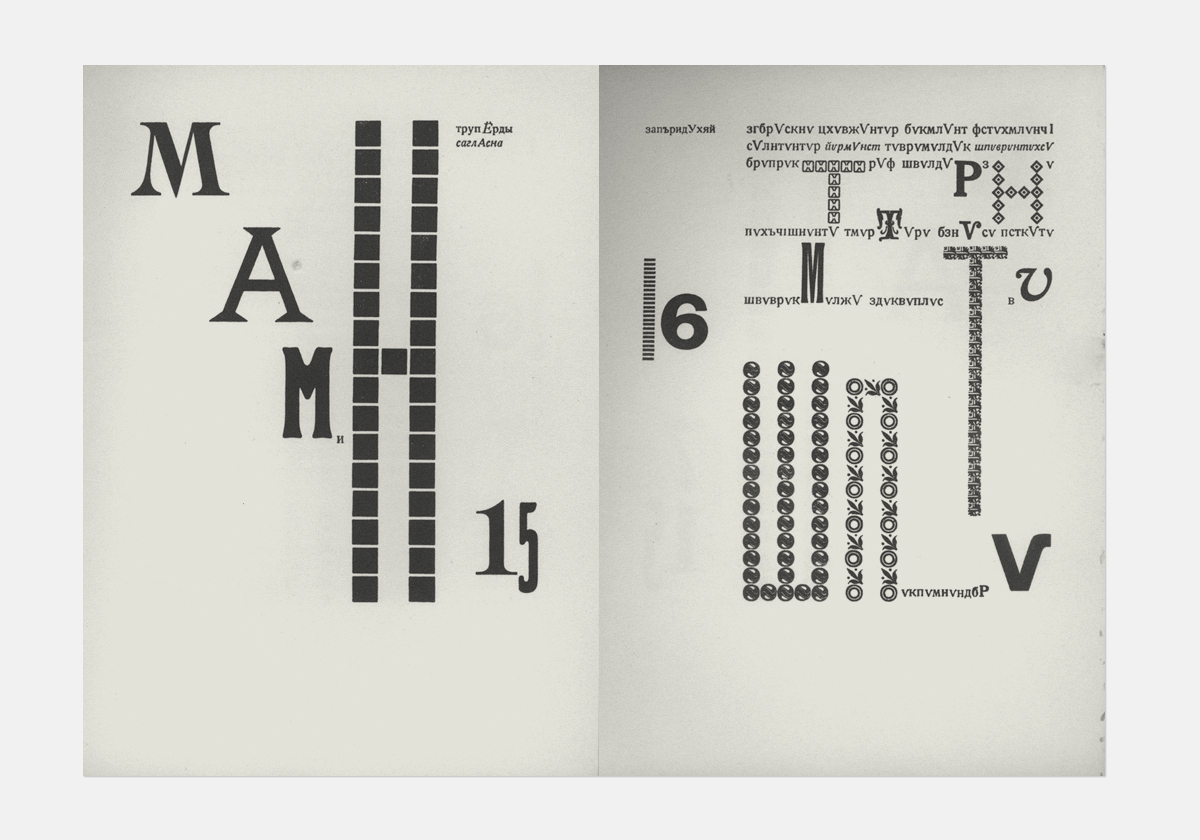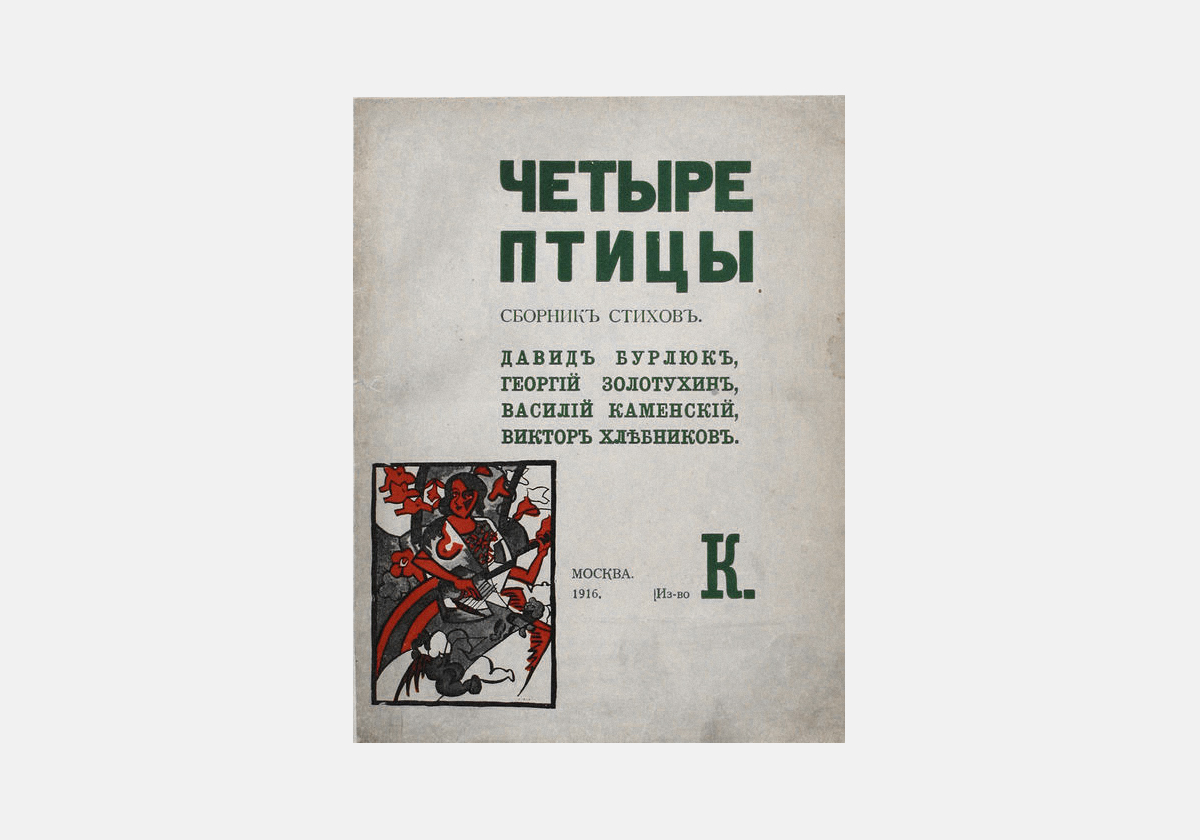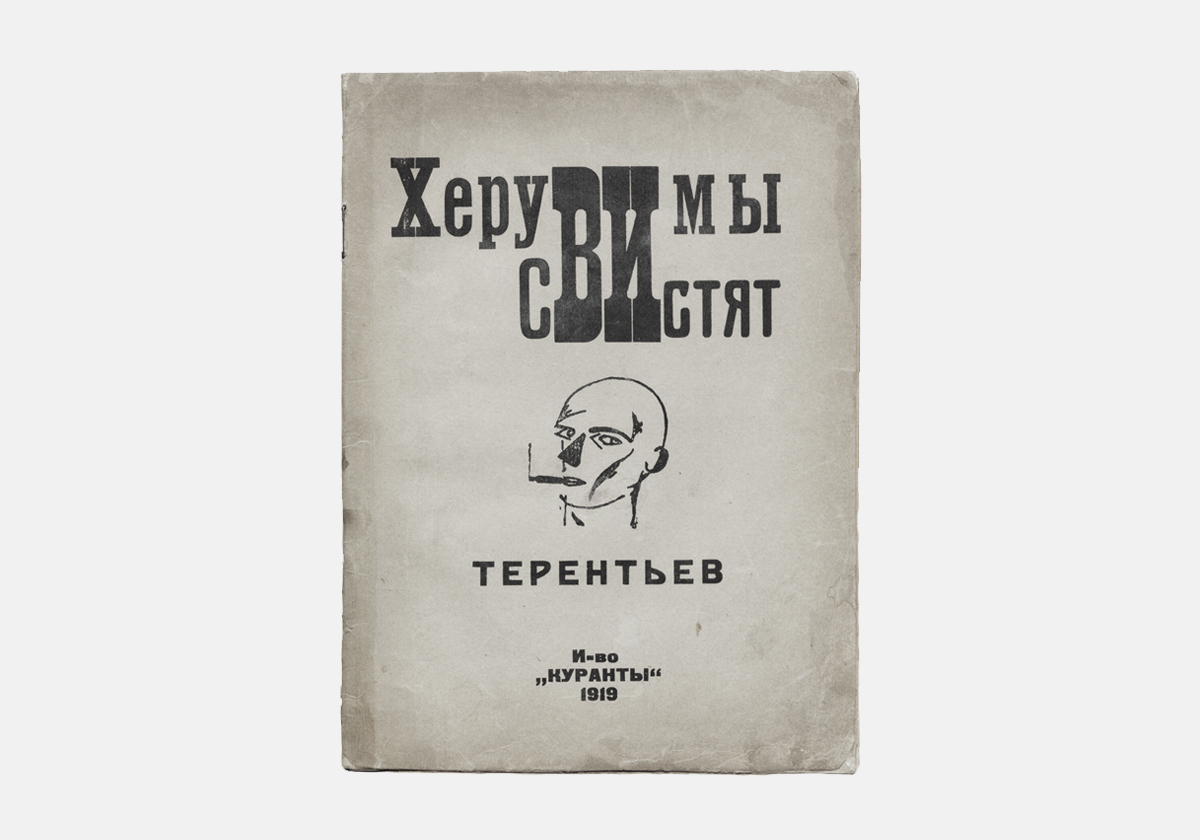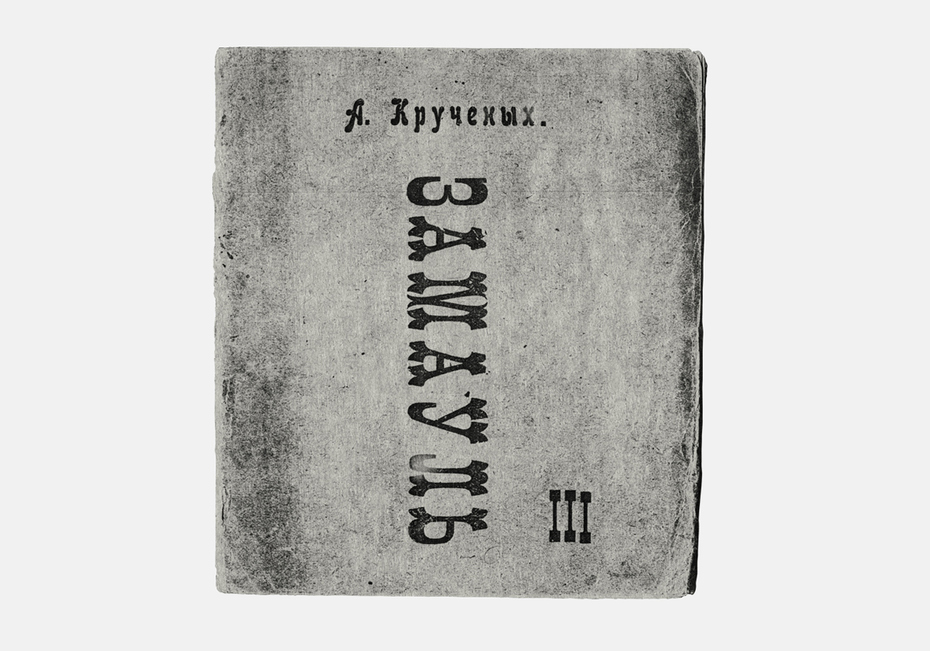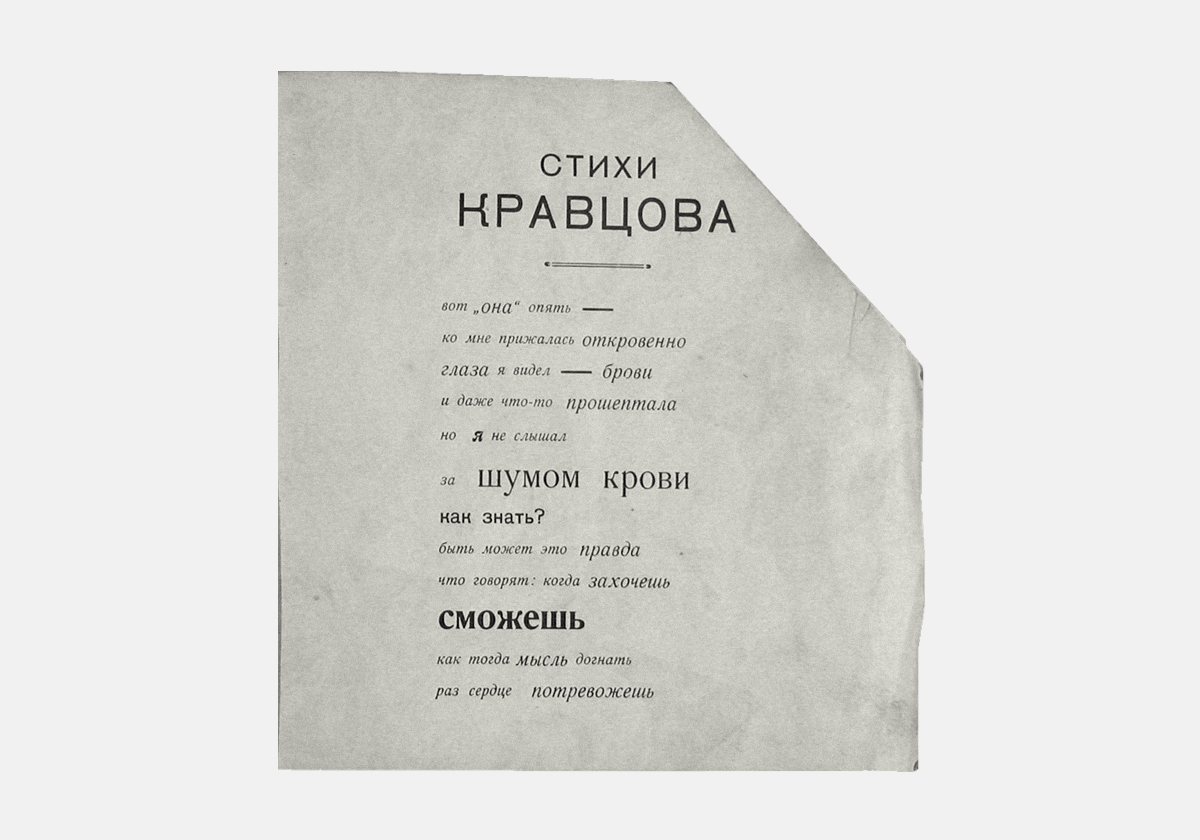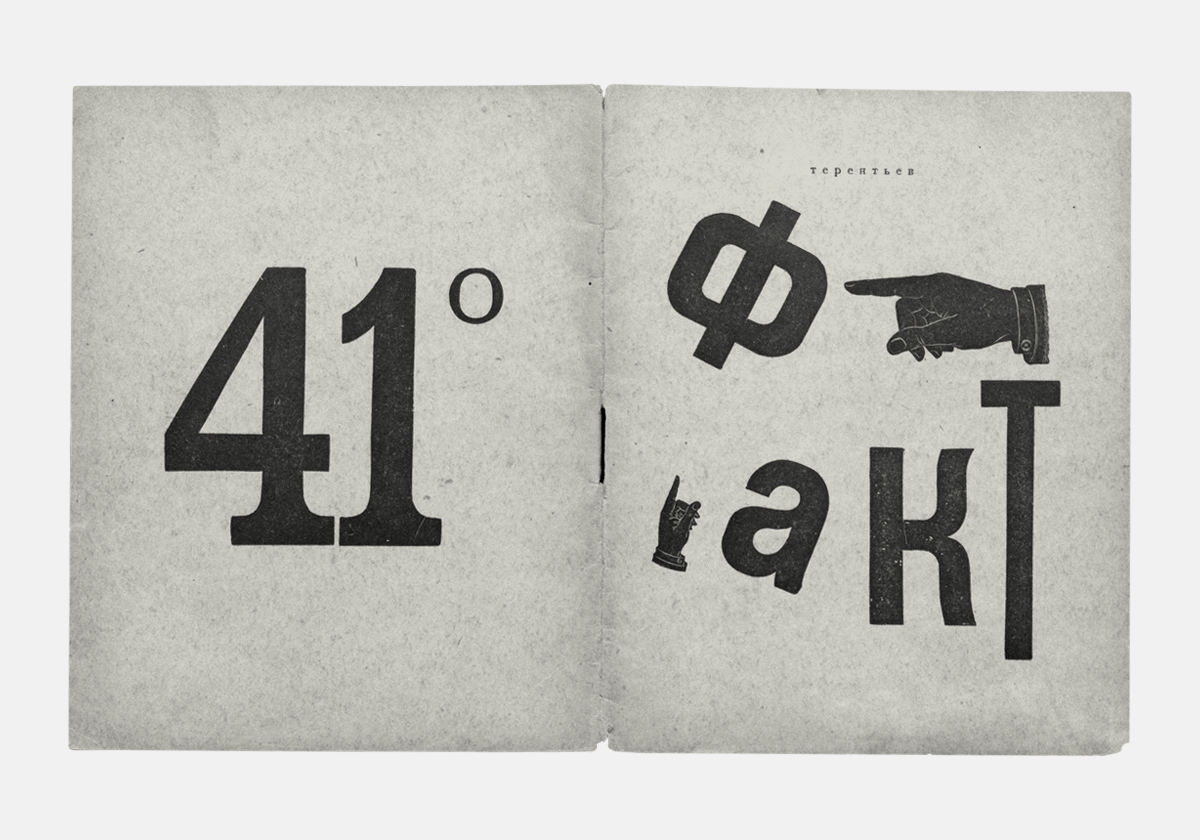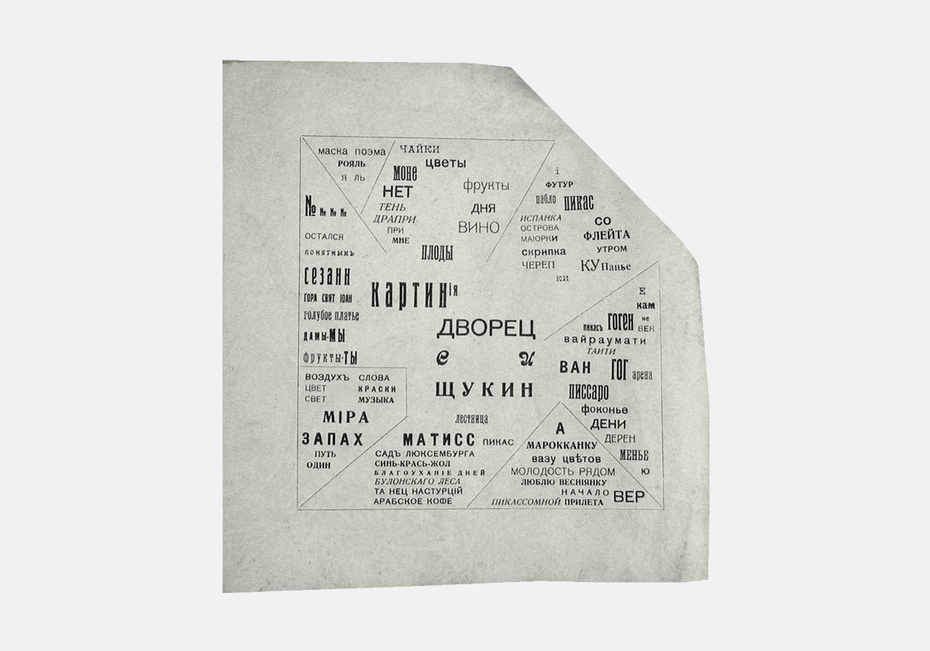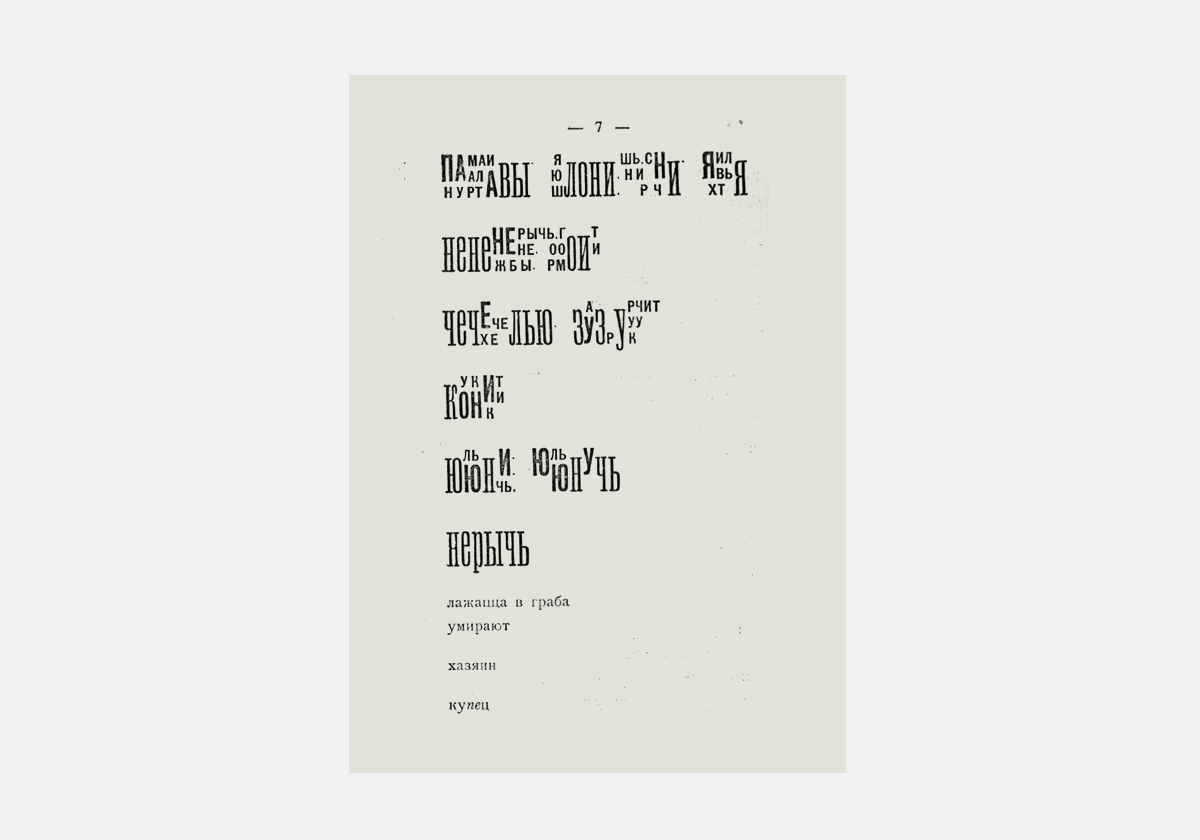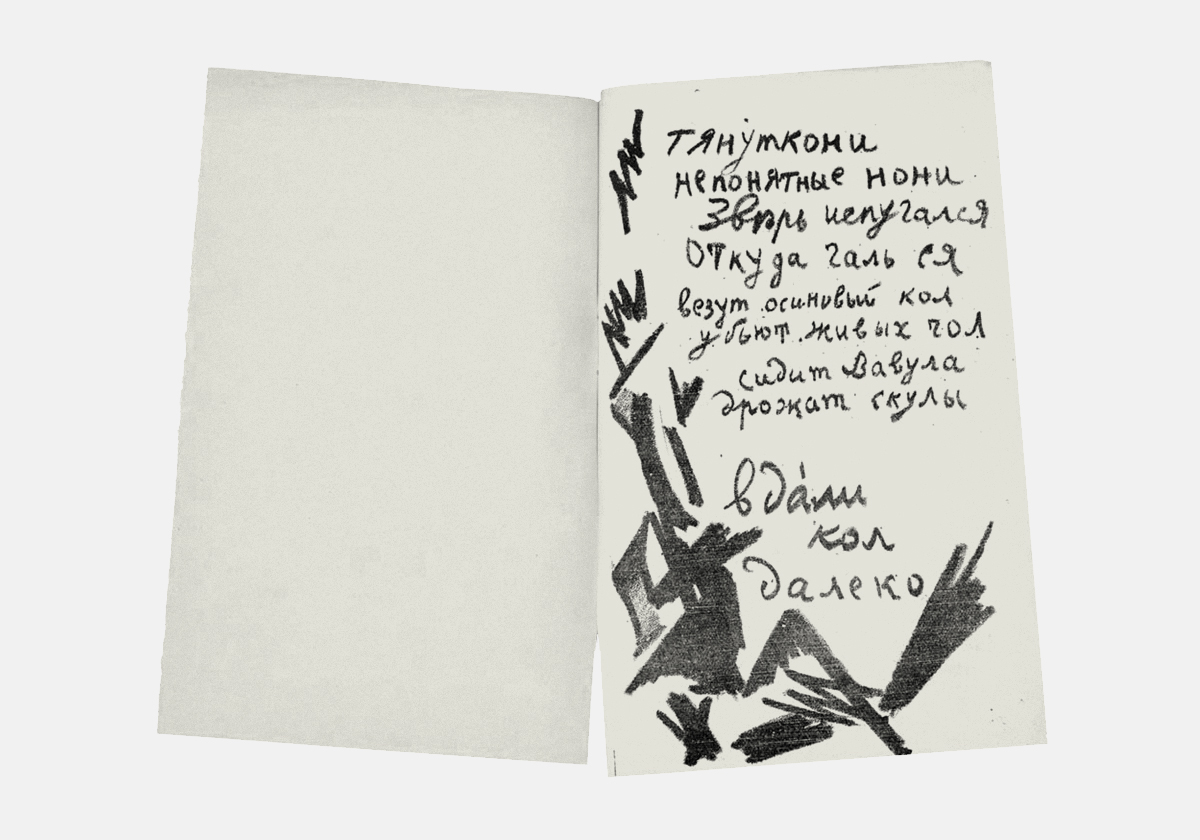
Типографика футуристов
на взгляд типографа*.
Часть вторая
Владимир Кричевский
итателю предлагается вторая часть статьи, написанной Вла­ди­ми­ром Кри­чев­ским, ав­то­ром из­вест­ных книг «Ти­по­гра­фи­ка в тер­ми­нах и об­ра­зах», «Пе­чат­ные кар­тин­ки ре­во­лю­ции», «По­э­ти­ка ре­про­дук­ции», «Мо­дерн(ъ) в пе­ча­ти», ис­сле­до­ва­те­лем рус­ско­го гра­фи­че­ско­го ди­зай­на на­ча­ла XX ве­ка. Первая часть статьи была опубликована в журнале в прошлом году.
"Типо" versus «лито»
Как графические техники типографика и литография — старые конкуренты.
Небывалое оживление в типографике XIX века косвенно связано с изобретением и развитием литографии. «Когда литография помимо приготовления новых образцов, сделавшихся необходимыми в общежитии благодаря удобству выполнения, начала отнимать у типографа его старые работы, к которым он давно привык, последний собрался с духом и бросился в бой со своей сестрою, в бой, становившийся всё более и более жестоким», — так писалось в 1900 году в популярном пособии по акциденции.
Действительно, многие наборные шрифты и орнаменты создавались тогда по образу и подобию литографированных, а вместе с вычурными буквами заимствовались и прихотливые формы построения надписей. Овальные, извилистые, ломаные, косые, поперечные строки стали обыденными. Металлический наборный материал подвергался известному насилию, что давало повод говорить об упадке типографского искусства. «Это всего лишь обманчивая имитация литографских эффектов посредством типографики, мнимая победа типографики над литографией», — заметил Ян Чихольд, комментируя французский типографический альбом 1862 года.
К началу XX века «упадок» стал ощущаться ещё острее, и футуристы словно бы решили взять реванш за мнимое поражение литографии, отменив типографику, образно говоря, росчерком литографского карандаша: из-под пера в печать, минуя набор.
Был в этом, разумеется, и другой смысл: желание предельно сблизить фактуры текста и рисунка, забота о передаче «движения души» пишущего, наконец, заманчивая возможность сосредоточить весь графический процесс в руках художника.
Протестуя против якобы холодного и обезличивающего набора, одни (Ларионов, Гончарова) воспользовались почти своим почерком, другие принялись форсировать небрежность и инфантильность письма, стараясь написать как можно косее и «каракулеватей» (больше всех в этом преуспел Крученых), третьи — это уже «лино» — гравировали на линолеуме, не стремясь превысить класс работ школьников с ластиками, четвёртые изобретали нарочито странные «принтскрипты» (как, например, Каменский в «железобетонах» тифлисского сборника 1918 года).
Артистизм этих опытов не стоит переоценивать: некоторые авторы «зависли» между живым и нарочито корявым почерком, доказав тем самым, что и антикаллиграфичность требует каллиграфической хватки (Взорваль — 1913, Тэ ли лэ или, например, хлебниковский Изборник работы П.Н. Филонова — обе 1914).
Коротенький экскурс в футуристическое «литописьмо» нужен, чтобы оттенить
достижения нескольких героев, отдавших предпочтение набору.
Отказ от набора — сильный «одномоментный» жест. То, что предлагалось взамен, можно найти и в черновиках пылких авторов (хотя бы у Пушкина), и в конспектах неаккуратных студентов. Тем же, кто выбрал набор, предстояло нарушить его вековые устои, учинить «типографскую революцию», оставаясь в круге технических приёмов и материалов типографики.
Многочисленные книжки Крученых выходили как в «автографированном», так и в наборном виде. Сравнивая два варианта его Лакированного трико (1919) — гектографированный и типографский (И. Зданевич), — Дж. Янечек заключает: «Под одним названием объединены антиподы издательского искусства: „минимал“ — скромный, рукодельный, почти по-детски бесхитростный буклет и „максимал“ — взлёт (a tour de force) типографического мастерства».
Чтобы уловить прелесть даже простейшего набора, полезно сопоставить два опуса Каменского, схожих по композиции и приправленных крупной буквой «К»: рукописный Клинок из сборника 1918 года и наборный Камень из Звучали веснеянки (1918).
Василий Каменский. Рукописный «Клинок» и наборный «Камень», оба 1918.
«Типо» ценнее «лито», как преодоление материала ценнее отказа от него, как опечатка — в логике футуристов — ценнее описки. Мне представляется, что задача «типофутуристов» была сложнее, а их работы с текстом — ярче и радикальнее. Ломая всяческие нормы, они подбирались к колыбели современной типографики, но при этом адаптировали тот старый опыт, против которого выступали. В очередной раз убеждаюсь в плодотворности метода "клин клином".
"Соблазн афиш«
Так в сборнике Софии Георгиевне Мельниковой. Фантастический кабачок
(дальше — просто Фантастический кабачок) назван раздел поэтессы Татьяны Вечорки. Стихи о театре и не футуристические. Но в типографическом контексте сборника пару слов на совершенно чистом развороте легко превратить в формулу содержания статьи о типографике.
Разворот из коллективного сборника «Софии Георгиевне Мельниковой. Фантастический кабачок». Тифлис: 41°, 1919.
Художники, способные прочитать «на чешуе жестяной рыбы <...> зовы новых губ», сторонники «всёчества» (и «ничевочества») — разве могли они не вдохновляться печатными эфемерами? И не только крупнейшими из них — афишами, но и всякими билетами, ярлыками, объявлениями. Например, объявлениями из отмеченного Владимиром Поляковым «Кине-журнала»: «Стоит нам только открыть любой номер этого журнала <...> как мы окажемся погружёнными в настоящую лабораторию по экспериментированию со всевозможными формами типографского шрифта. Речь идёт, конечно, о кинорекламе, занимавшей почти половину журнала. Обращает на себя внимание не только разномасштабность и многообразие шрифтов, но и их своеобразное расположение на поверхности листа, включавшее даже диагональные и круговые формы. При том внимании, с которым футуристы относились ко всем проявлениям массового вкуса, трудно рассчитывать, что они могли пройти мимо столь необычного источника».
Так ли уж он необычен? Ведь Поляков, в сущности, даёт описание эклектичного и разухабистого стиля типографики начала XX века, беря его в состоянии эссенции.
Это состояние лучше всего передалось, пожалуй, 17 ерундовым орудиям И. Терентьева (1919). Янечек находит его (или его произведений?) типографику «относительно (относительно литературы. — В. К.) произвольной». Тем интереснее она в рамках нашей темы: оторванная от собственно литературы, типографика становится «как таковой». Каждое орудие (страничка), включая и 13-е, которое «никогда не употребляется», суть афишка или, беря во внимание несомасштабно крупные буквы и тонированную в массе бумагу, выисканный фрагментик той самой афиши начала века.
Иного дано не было. Низвергать устои приходилось, соблазняясь низвергаемым. Младенчество типографического модернизма проявлялось в повторении форм «упадка» и стиля модерн, но — в каком-то огрублённом, сниженном, пародийном виде.
К тифлисским изданиям это относится менее всего, но обложки и титульные листы большинства наборных футуристических книжек середины 10-х годов напоминают по композиции обычные титульные листы. Всё те же центричная компоновка и трёхчастное членение по вертикали, всё то же построчное смешение разных шрифтов. Но есть какой-то обертон или, пользуясь излюбленным словом футуристов, сдвиг: то буквальный сдвиг какого-нибудь элемента вбок (например, на обложке Четырёх птиц (1916) в стороны разъехались картинка и данные о месте издания), то сдвиг всей симметричной конструкции с оси «изобразительной» поверхности (как в Заумной гниге, 1915), то — повсеместно — смещение заголовка по вертикали с благородного оптического центра; то английская строка, да ещё и лиловая (Дохлая луна, 1913); то акцентирование неглавной строки (гриф «футуристы» в ряде изданий), то, наконец, особое, диссонирующее оформление самого заголовка (слишком по-конструктивистски, буквами разных шрифтов или одного, но вызывающего: Изборник, Ряв! Перчатки — оба 1914, Тайные пороки академиков — 1916, Херувимы свистят — 1919 и ряд других).
И всё это — подчёркиваю ещё раз — при сохранении старой компоновочной схемы! Во внешнем оформлении футуристических книжек худосочный титульный лист как бы скрещивался с броской афишей. Результат скрещивания выказывал и поэтическое безразличие к форме, и благотворный (для той типографической эпохи) непрофессионализм, подтверждающий «вмешательство» поэтов и художников в дела наборщиков и метранпажей.
Через пять-десять лет, перейдя в стан конструктивистов, некоторые бывшие футуристы станут презирать реалии предреволюционной типографической культуры. Но пока в ход шли даже самые вычурные шрифты модерна. Имя Алексея Крученых на шмуцтитуле сборника Молоко кобылиц (1916) набрано печально знаменитым шрифтом Гейша. В контексте модерна это, возможно, выглядело обворожительно. Здесь же налицо стремление спутать типографические значения, впрочем, вместе с каким-то порочным любованием шрифтовыми реалиями времени.
Футуристы знали его шрифтовую палитру. И среди вдохновлявших их вещей наверняка были и образцы шрифтов, издававшихся как словолитнями, так и всеми уважающими себя типографиями. Страницы этих редких изданий заполнены обрывками фраз и слов, набранных разными, иногда неестественно крупными шрифтами. Чем не готовые футуристические творения?
И раз уж я подступил к атрибутам типографии, нельзя не вспомнить о реалиях самого печатного процесса. Для пробных и приладочных листов нередко используют макулатурную бумагу, и после нескольких прогонов на них слоями краски могут лечь друг на друга даже разные культурные слои. Эти листы заставляют дизайнеров преклоняться перед графическим гением простой случайности. Так вот, один из ранних опытов поэтизации наложения при печати — обложки книг А. Крученых Миллиорк (1919) и Лакированное трико. Отпечатанные в два прогона с одной наборной печатной формы с поворотом на непрямой (!) угол, эти работы Ильи Зданевича блестяще предвосхищают эпоху конструктивизма. Однако мне снова пришлось забежать в Тифлис. В московских и петроградских «типо-изданиях» если изредка и происходило что-то из ряда вон выходящее, то скорее на рядовых страницах, попавших под куда более традиционную обложку.
Алексей Крученых. Обложки «Лакированное трико» и «Миллиорк», обе 1919.
Одно из откровений — страницы книги Маяковского Владимир Маяковский: трагедия (1914). Её оформление и Янечек, и Сьюзан Комптон приписывают Давиду и Владимиру Бурлюкам. Причём вторая обращает внимание на «самую влиятельную из книг как объектов дизайна», а первый, соответственно своему профилю, снова, как и в случае с Терентьевым, фиксирует декоративное значение крупных и жирных букв, вкрапленных повсюду «без какой-либо выразительной и практической цели». Оба автора не замечают «слона» пространственной организации. Но пробелы и поля значат для типографа не меньше, чем «букашки»-буквы. В «Трагедии» два прорыва в типографику наших дней. Во-первых, стихотворные строки набраны с единым и таким крупным интерлиньяжем, чтобы никакая слишком крупная буква не нарушила типометрику (как это случится у Каменского). Во-вторых, полосы на каждом развороте стоят не зеркально, а переносно-симметрично. Это значит, что расширенное поле с обильными маргиналиями появляется всё время слева от текста, независимо от фактора чётности-нечётности страницы.
Надо отдать должное этому изобретению (?), применённому и в некоторых других изданиях стихотворных сборников, где очень короткие строки чередуются с длинными. В этом случае велик резон верстать стихи на одном и том же расстоянии от левого края страницы. Прежде же было принято центрировать каждое стихотворение, сообразуясь со средней шириной «пятна».
С именами Маяковского и Д. Бурлюка связано по крайней мере ещё одно типографическое откровение: единственный номер журнала Взял: барабан футуристов (1915). Заурядные страницы, но какая обложка! У верхнего края стоят четыре буквы, набранные настоящим афишным (деревянным) Герольдом (эта гарнитура — символ эпохи) размером в 8 квадратов и оттиснутые на сугубо обёрточной бумаге. Типограф (не сам ли Маяковский?) соблазняется афишей и одновременно преодолевает соблазн предельной лаконичностью своего решения. Высоту Взяла (Каменский умудрился просклонять этот глагол) не брал в России, кажется, больше никто.
Взял: Барабан футуристов. Павлоград, 1915.
Шрифтовое ассорти и «нестрочье»
Нет, не образ Взяла, а нечто прямо противоположное всплывает при первой мысли о типографике футуристов.
Смена шрифта при переходе от строки к строке акцидентной вещи вряд ли кому-нибудь кажется странной. Тем более не казалась в начале века. Футуристы сделали два следующих шага: «перемешали» старую композицию и тем самым добились теснейшего соседства букв разных гарнитур, начертаний и типоразмеров внутри одной строки и даже отдельного слова. Композиция измельчилась, превратилась в пёструю фактуру. В результате подключки буквы переставали держать базовую линию, начинали скакать. От смеси скачущих букв недалеко до «нестрочья». Этим замечательным словом А. Крученых обозначил свободный полёт букв и слов в одноимённой гектографированной брошюрке (1917). Картинная композиция из словесного материала равнозначна — по Ю. Герчуку — освобождению текста от линейной, временной последовательности. В сочетании со шрифтовой смесью это и есть вектор развития футуристической типографики.
Яркий пример шрифтового ассорти, ещё и обогащённого нестрочьем, являют афиши гастрольной поездки футуристов по России в 1914 году. Известны по крайней мере два её варианта — казанский и тифлисский. При заурядной, совпадающей до наложения компоновке они отличаются только курьёзно разными смесями. Это, видимо, означает, что казанский вариант был образцом для тифлисского. Требовалось (или требовал иной ассортимент шрифтов в типографии) изменить его на «молекулярном» уровне, так что в двух афишах при некотором совпадении кегельного ритма (!) трудно найти хотя бы две полностью совпадающие литеры. Смена смеси не меняет даже фактуру набора, и, таким образом, несмотря на титанический труд наборщика, облик афиши существенно не изменился.
Из наблюдения за студенческими опытами знаю, что не слишком перспективные дизайнеры начинают сразу с «эксперимента», и это не что иное, как шрифтовая смесь из журнальных вырезок. Не каждый знает про футуристические «фокусы». Просто это самый наивный и лёгкий путь достижения некоторого эффекта. Как живое существо (по Дарвину) проходит в своём развитии через все стадии эволюции видов, так и постижение экспрессивных качеств набора начинается с возвращения на раннюю стадию эмбрионального развития модернистской типографики.
Так действовал и Каменский (или его ассистент), но, будучи пионером, никуда не возвращался. Знаменитые книжки Нагой среди одетых (1914) и особенно Танго с коровами обрушивают на зрителя лавину удивительных качеств. Обложка с этикеткой, попавшей под обрез, и парным контрастом между заголовочной (сверху) и авторской (снизу) группами текста сделает честь любому постмодернисту. Здесь всё сразу: и пятый угол, полученный путем упразднения «четвёртого», и квадратный формат, и обои, и апофеоз нестрочья — несколько поэм, где вместо «строкосмыслов» — мозаика из разных по форме и размеру «словоблоков». Однако о характере набора можно сказать только два слова — шрифтовая смесь. Лишённая фона (выделено всё), довольно аморфная, такая смесь для глаза отнюдь не взрывоопасна. Слышать от автора о «чёткости» и «чтении, как по нотам» довольно странно. Подробный анализ у Янечека также не представляется убедительным. Типографика «железобетонных» поэм свидетельствует больше об энтузиазме, чем о графической
дисциплине.
Соперник Каменского Илья Зданевич отзывался о необычной книге весьма скептически: «В некоторых отношениях она любопытна, но едва ли более, так как подобный приём творчества уделяет слишком много места глазу, то есть ищет в ненадлежащем месте и поэтому едва ли многое найдёт».
Через десять лет Ильязд уделит глазу ещё больше места.
"Набор писаки«
На титуле книги Ильи Зданевича Лидантю фарам вслед за словами «аблошка Наума Грановского» (этот коллаж, кстати, выглядит несколько чужеродным книге) стоят слова, вынесенные в название главы. Впервые в практике русских футуристов столь определённо заявлено о типографическом авторстве: сомнений относительно второй, а может быть, и главной профессии Ильязда не остаётся.
«Я потратил немало часов своей печальной жизни на вставку малюсеньких свинцовых брусочков между тысячами литер, прошедших через мои пальцы» — так писал Ильязд в своих заметках Пятьдесят лет спустя. О том, что он был типографом в полном смысле слова, говорят не только его собственные признания.
Ильязд за набором в L’imprimerie Union, Париж, 1962.
Фото: Мишель Одер (из книги «Iliazd and the Illustrated Book». Нью-Йорк: Museum of Modern Art, 1987).
Почти все авторы, пишущие о футуризме, сходятся в том, что все имена «лучистых поэтов», чьи работы даны в статье С. Худакова из сборника Ослиный хвост и Мишень (1913), как и имя автора статьи, — вымысел И. Зданевича. Если так, то самые ранние футуристические эксперименты с набором предприняты (до Маринетти) именно им.
Возможно, мы бы знали больше об отношении футуристов к зримому слову, будь опубликованы доклады, прочитанные И. Зданевичем в 1918 году в тифлисском «Фантастическом кабачке». Согласно списку, приведённому в «кабачке»-книге, они назывались так: Правописание и потуги букв и Магнетизм букв и годовщина Кабачка. В докладах других заумников, судя по названиям, эта тема не затрагивалась.
Илья Зданевич вернулся в Тифлис сразу после Октябрьского переворота и незадолго до основания издательства «41°» побывал в учениках в нескольких типографиях. Был ли среди его учителей А. Тернов? О последующем сотрудничестве с ним Зданевич сообщит: «Следуя моим указаниям, типограф Андриан Тернов выполнил набор всех книг, изданных под маркой „41°“ в 1919 и 1920 годах».
Конечно, два других члена триумвирата «41°» — Терентьев, «стоявший на плечах Зданевича», и Крученых — не могли не внести свою лепту в графическое оформление по крайней мере своих произведений, о чём свидетельствует отметка в колофоне Фантастического кабачка: «Набирал Адриан Тернов, правили Терентьев, Алексей Крученых, Илья Зданевич». Однако вышеприведённое утверждение Ильязда согласуется с данными каталогов ряда его выставок. Во всяком случае, «чуть-чуть» было безусловно за ним, и печать типографического мастерства Ильи Зданевича стоит и на книгах Терентьева (Рекорд нежности — 1919, 17 ерундовых орудий, Факт, Трактат о сплошном неприличии — 1920), и на обложках Замаулей Крученых, и, конечно, на изданиях произведений самого типографа.
Зданевич издал цикл из пяти драматических произведений («виртеп ф 5 действах») под общим названием Аслаабличья. Четыре «действа» вышли отдельными книжками (одна — в Париже, и о ней речь особая), а одно вошло в сборник Фантастический кабачок.
Выполненное не без библиофильского смака, оформление «действ» суховато и, можно сказать, функционально. Зданевич методично ищет способ фонетической (как слышится) записи зауми, для чего выделяет ударные слоги или гласные: то полужирным шрифтом (Янко круль албанскай — 1918), то курсивом (Остраф пасхи — 1919), то, наконец, прописными (Асёл напракат — 1919 и Зга якабы — 1920). Здесь же вырабатывается особая система «оркестровой» записи. Пучки строчек, «перевязанных» крупными литерами, там, где во всех голосах одна и та же буква, действительно напоминают музыкальную нотацию.
Как курьёз стоит отметить эпизод отказа от набора. Клишированный заголовок «Остраф пасхи» можно назвать осмысленной пародией на набор. Нечто подобное встретится на изумительной литографированной афише парижского доклада Зданевича Илиазда: элога Ильи Зданевича, прозванного ангелом (1922), где некоторые буквы, как бы разрезанные и поданные со смещением частей друг относительно друга, провоцируют мысль о наборе или коллаже.
Фантастический кабачок, в который Зданевич включил третью часть своей пенталогии, а именно Асёл напракат, вобрал в себя лучшие качества изданий «41°».
В оформлении этой, кажется, самой толстой книги русского футуризма (192 страницы) авангардистский натиск сочетается с элегантностью. В томике есть на что посмотреть, включая знаменитую типографическую картину И. Зданевича Зохна и женихи, показывающую, насколько осмысленной может быть шрифтовая смесь. Больше всего, однако, поражает редакционно-издательская концепция сборника, и, поскольку она дана в сильных типографических признаках, на этом стоит остановиться.
В Кабачке никаких предисловий и комментариев, но есть развитый аппарат.
В алфавитном списке участников сборника не забыт единственный Аноним, хотя это всего лишь автор старинной миниатюры, репродукция которой сопровождает статью о грузинских манускриптах. Эта статья и несколько других «обычных» текстов стоят в одном ряду с типографически напористой заумью. Грузинские и армянские стихи даны без перевода. Все авторские разделы, а также и вышеупомянутый список докладов, как, впрочем, и каждая из вклейных репродукций, входят в сборник на равных. У каждого раздела — своя типографическая характеристика, сочетающаяся со сквозным принципом подачи материала. В колофоне кроме наборщиков указаны все печатники и переплётчики. Сборник незарубрицирован.
Чем не реализация концепции «всёчества» Ларионова и Зданевича? В советское время жанр открытого книжного пространства был, естественно, утрачен.
Фантастический кабачок — лучшая из вещей, изданных на широте Тифлиса. Но высшего типографического градуса Ильязду (имя и фамилия скрестились в 1920 году) предстояло достичь в Париже, куда он отправился в следующем году. Пятая часть Аслаабличий — Лидантю фарам — анонсировалась несколько раз: «пичатаеца». Но потому ли, что в Тифлисе что-то мешало, или, наоборот, исключительно благодаря «парижачьему» воздуху книга вышла в 1923 году.
Лидантю фарам — обязательный и не имеющий аналогов аттракцион в паноптикуме модернистской типографики. «Каждая страница этой книги, — пишет Франсуаза Лё Гри-Бергман, — представляет собой картину, чистейший „графизм“, демонстрирующий типографический репертуар, который не поддаётся инвентаризации. Более того, здесь столько игры, что не каждая страница поддаётся чтению».
В наборе задействовано три-четыре десятка популярных русских гарнитур того времени. Но Ильязду этого мало, и он добавляет гигантские буквы, составленные из наборных линеек и орнаментов. Почему же эта «адская» смесь производит вполне гармоничное впечатление? Во-первых, шрифтосмешение происходит на фоне клочков нормального книжного набора. Строки 10-го кегля задают линейный характер чтения, но глаз тут же включается в пляску крупных, жирных, чужих букв. Во-вторых, всё это происходит на страницах со сквозной и довольно жёсткой пространственной организацией: широкое поле снизу (излюбленный приём Ильязда) и почти квадратная полоса с узкой колонкой маргиналий. В-третьих, типограф строго контролирует каждую пару букв, чужеродных друг другу, но оказавшихся рядом.
Если можно назвать Лидантю фарам типографическим спектаклем, то главные его действующие лица — колонцифры. Они входят в колонку маргиналий, скачут по её высоте, достигают невероятных размеров и иногда бесцеремонно вторгаются в зону основного текста. По двузначным колонцифрам (в книжке 62 страницы) особенно хорошо заметна способность Ильязда подбирать самые несовместимые, а потому и прекрасно — по принципу парного сверхконтраста — сочетающиеся шрифты.
«Появление „ЛидантЮ фАрам“ знаменует завершение „пламенного“ периода творчества Ильязда». По выходе книги автор писал так: «Это высшая точка. И достигнув её, я бросаю эту книгу. Прощай, молодость, заумь, долгий путь акробата, экивоки, холодный ум, всё, всё, всё».
...Начиная с 1940 года из той же парижской типографии «Унион» начнут выходить de luxe editions книг художников — Брака, Джакометти, Матисса, Миро, Пикассо, Сюрважа, Эрнста и других. Их издатель, оформитель, а иногда и автор — Iliazd, французский типограф и поэт русско-грузинского происхождения. Почти все они будут набраны одним изысканным шрифтом Gill Sans одного кегля. И только прописными. Типографический поиск сведётся лишь к пространственной организации текста за счёт пробелов. Последняя из ряда книг выйдет в 1974 году, за год до скоропостижной (в возрасте восьмидесяти одного года) смерти издателя.
В этих вещах непросто узнать Илью Зданевича периода футуристического натиска. Впрочем, в употреблении только прописных букв усматривают традицию оформления духовных текстов его родной Грузии.
Эту свою фотографию Ильязд прислал матери из Франции. 1930-е годы.
* Сло­ва при­зна­тель­но­сти — Ана­то­лию Бо­ров­ко­ву, биб­лио­гра­фу и со­би­ра­те­лю фу­ту­ри­сти­че­ских ред­ко­стей, поз­во­лив­ше­му мне по­ли­стать те са­мые книж­ки, ко­то­рые не мог­ли не при­ве­сти к мыс­ли о ни­же­сле­ду­ю­щей ста­тье. Осо­бая бла­го­дар­ность из­да­те­лю Сер­гею Куд­ряв­це­ву, ко­то­рый не пре­ми­нул снаб­дить ме­ня со­от­вет­ству­ю­щей ли­те­ра­ту­рой по те­ме и под­ска­зал не­сколь­ко по­лез­ных ци­тат. Од­на из них ока­за­лась не­за­ме­ни­мой для эпи­гра­фа.
Библиография
1. Ковтун Е. Ф. Русская футуристическая книга. М.: Книга, 1989.
2. Iliazd. Paris: Center Georges Pompidou, 1978.
3. I libri di Iliazd: Dall‘avanguardia russa alla scuola di Parigi. Firenze: Centro Di. 1991.
4. Iliazd. Ledentu le phare. Paris: Éditions Allia, 1995.
5. Кирилл Зданевич, Илья Здaневич: Каталог выставки. Тбилиси, 1989.
6. Авангард и традиция: книги русских художников XX века: Каталог выставки в Российской государственной библиотеке. М.: Даблус, 1993.
Чи­хольд Я. Об­лик кни­ги: Из­бран­ные ста­тьи о книж­ном оформ­ле­нии. М., 1980. С. 34.
Поз­во­лю се­бе со­слать­ся на соб­ствен­ную ста­тью Из-под пе­ра в пе­чать, ми­нуя на­бор (Ре­кла­ма. 1985. № 5. С. 17). Фу­ту­ри­сти­че­ские опы­ты в ста­тье не за­тро­ну­ты. Ме­ня ин­те­ре­со­ва­ло, как, за­чем и ка­кие по­чер­ки вво­дят ди­зай­не­ры в со­вре­мен­ную пе­чать, не пе­да­ли­руя сам при­ём.
Сло­ва Ма­ри­нет­ти. Об этом см.: По­ля­ков В. Рус­ский ку­бо­фу­ту­ризм: кни­ги и идеи. М., 1995. С. 107–113.
Janecek G. Op.cit. P.111.
По­ля­ков В. Указ. соч. С. 113.
Janecek G. Op.cit. P.119.
Ин­те­рес­но, что не­ко­то­рые ли­то­гра­фи­ро­ван­ные и гра­ви­ро­ван­ные кни­ги, как, на­при­мер, и эта, вы­шли в на­бор­ных об­лож­ках.
Так на­зы­ва­ли ак­ци­дент­ный при­ём сту­пен­ча­той (обыч­но в две-три сту­пе­ни) стро­ки. В сущ­но­сти, это та же «ле­сен­ка» Ма­я­ков­ско­го.
Мне, кста­ти, пред­став­ля­ет­ся, что со­вет­ский ти­по­гра­фи­че­ский кон­струк­ти­визм тем и при­вле­ка­те­лен, что не из­ба­вил­ся от ро­ди­мо­го пят­на ку­бо­фу­ту­риз­ма и так и не вы­шел на го­ря­чо де­кла­ри­ру­е­мый уро­вень «аэро­план­ной» чи­сто­ты и це­ле­со­об­раз­но­сти. Это­го уров­ня пред­сто­я­ло до­стичь за­пад­ным — не­мец­ким, швей­цар­ским, гол­ланд­ским — ти­по­гра­фам.
Compton S.P. Op.cit. P.84.
Janecek G. Op.cit. P.216.
Или, стро­го го­во­ря, от пра­во­го. Яне­чек об­ра­ща­ет вни­ма­ние на две кни­ги Ва­ди­ма Шер­ше­не­ви­ча, где стро­ки вы­клю­че­ны (то есть вы­рав­не­ны) по пра­во­му краю (Janecek G. Op.cit. P.153).
В Рос­сии до сих пор прак­ти­ку­ет­ся цен­три­ро­ва­ние сти­хов на стра­ни­це, и это об­ра­зец на­ци­о­наль­ной ти­по­гра­фи­че­ской кос­но­сти.
Под­ключ­ка, то есть сов­ме­ще­ние вну­три стро­ки шриф­тов раз­но­го кегля, бы­ла де­лом кро­пот­ли­вым, так как ме­тал­ли­че­ская пе­чат­ная фор­ма не вы­но­сит пу­стот. Ска­кать мог­ли да­же ли­те­ры од­но­го кегля, ибо то­гда ещё не был вы­ра­бо­тан стан­дарт ба­зо­вой ли­нии.
См.: Гер­чук Ю.Я. Ху­до­же­ствен­ные ми­ры кни­ги. М., 1989. С.102.
Ино­гда ак­ци­дент­ные ма­сте­ра кла­ли на на­бор­ную дос­ку точ­ный эс­киз и пря­мо на нём на­би­ра­ли, как по ша­бло­ну. В дан­ном слу­чае на дос­ке мог ле­жать пе­чат­ный про­об­раз афи­ши.
Цит. по: Le Gris-Bergmann F. Iliazd and the constellation of his oeuvre // Iliazd and the illustrated book. NY, 1987. P.38.
Со­глас­но Одри Ис­сель­ба­чер, на­зва­ние из­да­тель­ства (уни­вер­си­те­та ком­па­нии, груп­пы за­ум­ни­ков) озна­ча­ет «ши­ро­ту Ти­фли­са, со­дер­жа­ние ал­ко­го­ля в брен­ди и тем­пе­ра­ту­ру, вы­зы­ва­ю­щую бред при ли­хо­рад­ке» (Isselbacher A. Iliazd and the tradition of the «livre de peinte» // Ibid. P.12).
Цит. по: Le Gris-Bergmann F. Op.cit. P.24
Janecek G. Op.cit. P.189.
«Пи­ча­та­е­ца» — бы­ло обе­ща­но в 1919 го­ду. Не бы­ла ли кни­га хо­тя бы ча­стич­но на­бра­на в Ти­фли­се? Не при­вёз ли Ильязд в Па­риж проб­ные от­тис­ки?
Le Gris-Bergmann F. Op.cit. P.31.
Цит. по: Gayraud R. 1923 — De «Ledentu le Phare» aux «Parigots»: Il’a Zdanevic et la transformation de la «zaum» // За­ум­ный фу­ту­ризм и да­да­изм в рус­ской куль­ту­ре. Bern, 1991.